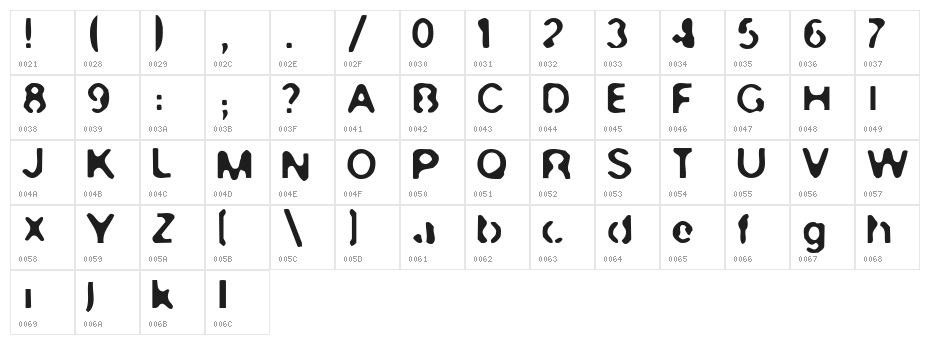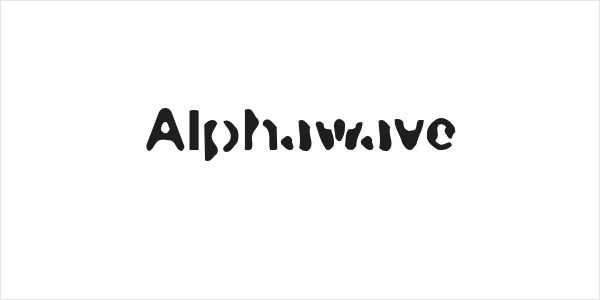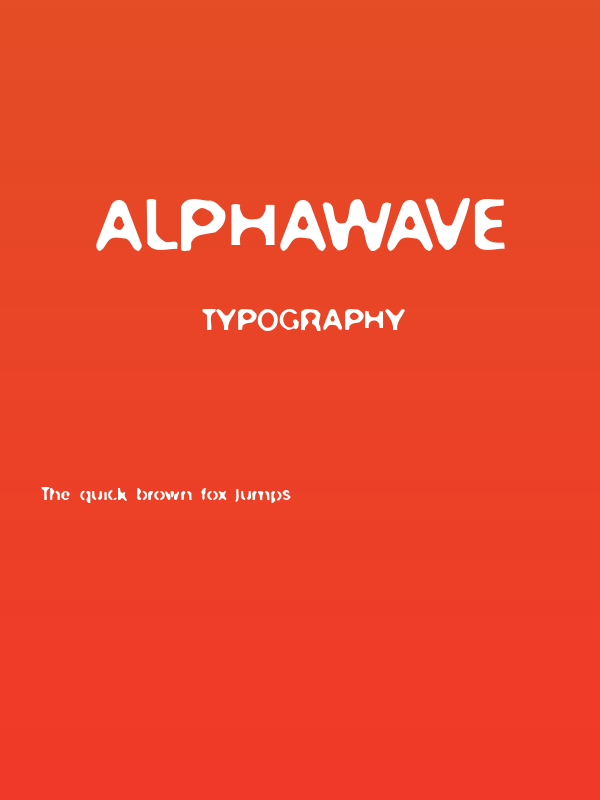
Alphawave Font
| Общий стиль | Playful, Energetic |
| Рекомендуемые проекты | Ideal for children's books, playful branding, event posters, and creative packaging. |